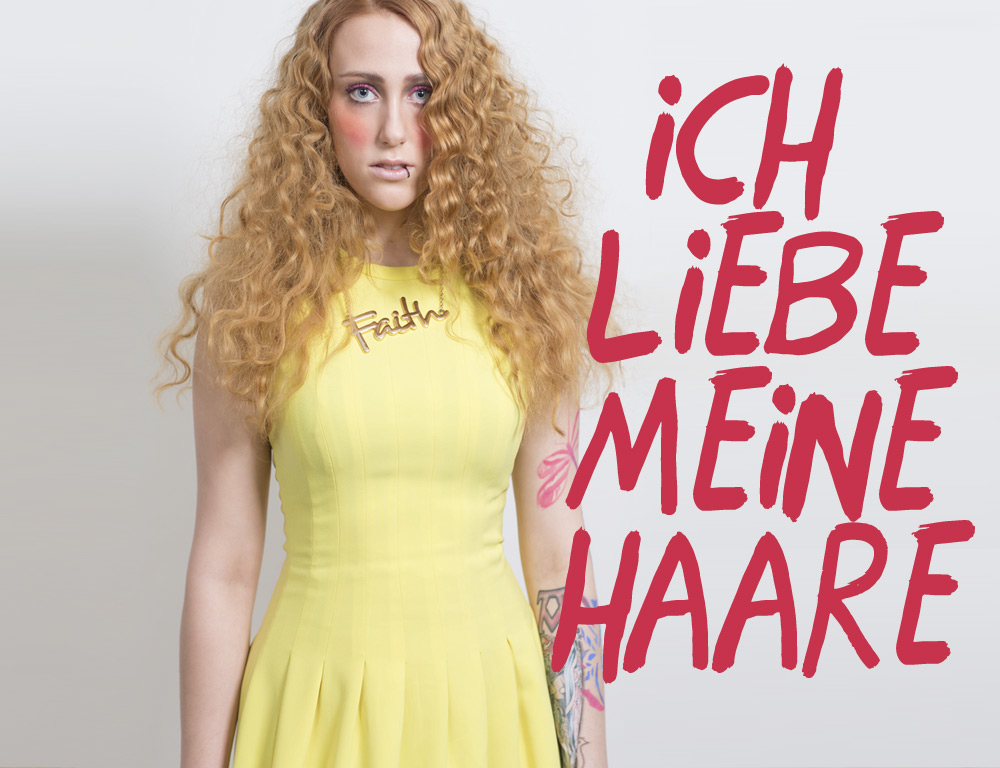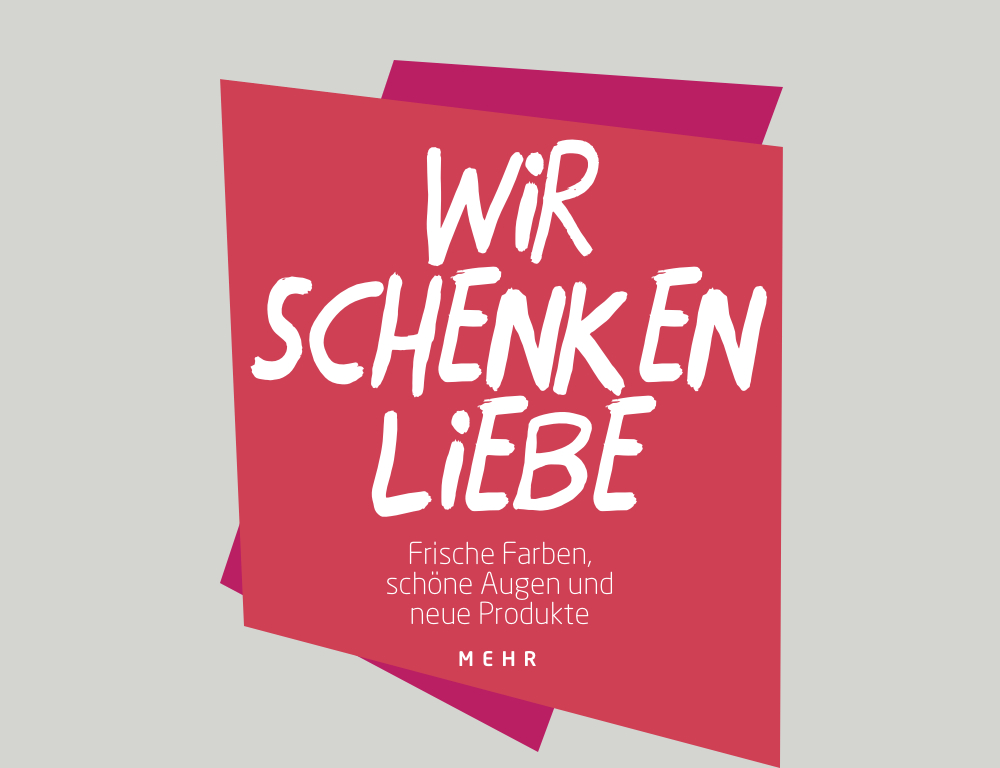
Pinsel Schrift / Handschrift
ich suche sehr dringend folgende Schrift ("Wir schenken Liebe"), die auf diesen Grafiken verwendet wird:
Verwendet wird die Schrift auf mehreren Grafiken dieser Seite: http://www.friseur-masson.de/
Hab schon viel Zeit damit verbracht, die Schrift auf vielen Font Seiten zu suchen. Vielleicht kennt sie jemand von Euch?
wenn ich bei diesen pseudo-handschriften immer die gleichen buchstaben sehe ohne das diese sich leicht voneinander unterscheiden (siehe: E oder A in Haare) läuft es mir persönlich ja immer kalt den rücken runter.
WIR SCHENK EN LIEBE finde ich ja fast schlimmer ...